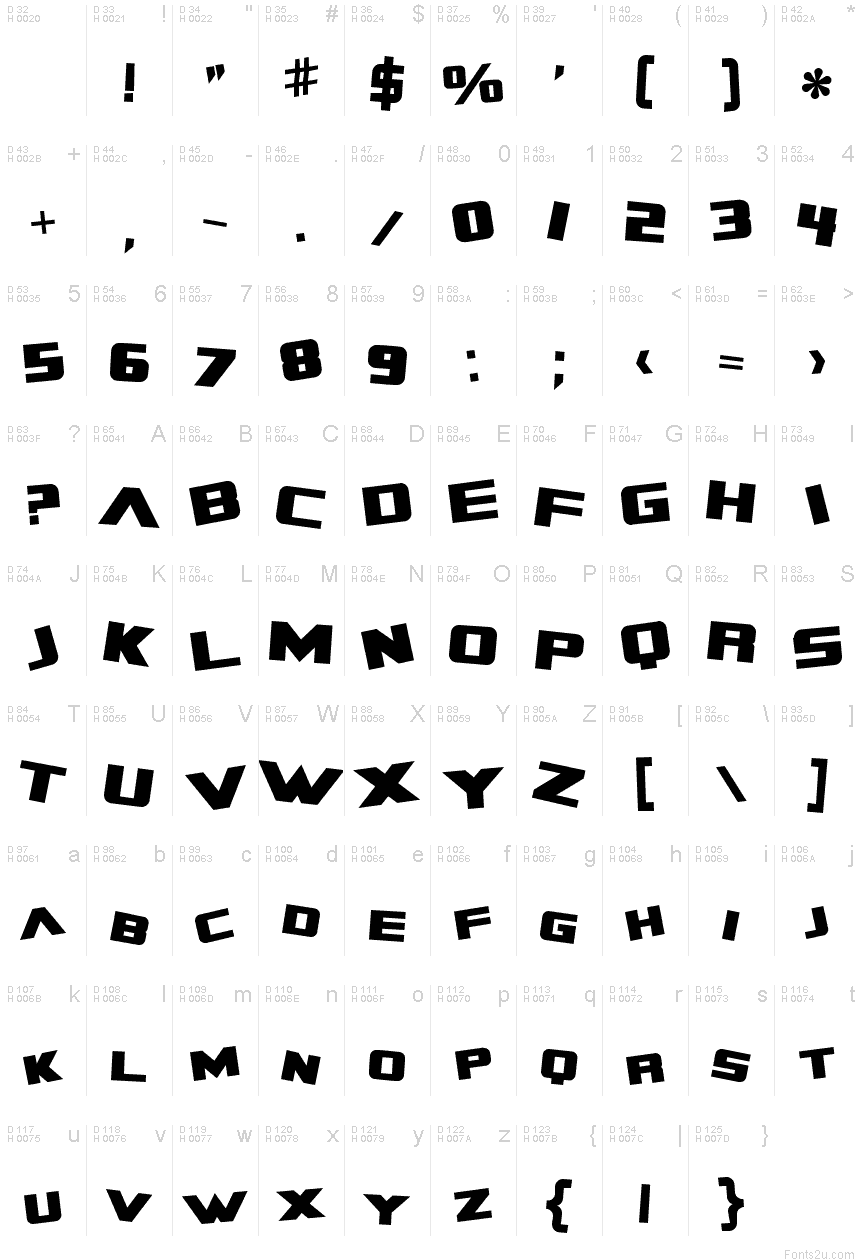
Zero Gravity Extended Bold von ShyWedge ist eine kostenlose Sci-Fi-Display-Schrift mit dem eigenwilligen Charme der Arcade-Ästhetik der späten 90er Jahre. Die Versalien sind breit, blockartig und leicht verzerrt; schräge Schnitte und eine unausgewogene Balance lassen die Schrift fast schwebend wirken, während ihre massiven Formen für Bodenhaftung und Ausdrucksstärke sorgen.
Damit eignet sie sich perfekt für Gaming-Logos, Sci-Fi-Poster, Mixtape-Cover, Zine-Überschriften und Titel, bei denen ein kurzes Wort einen energetischen, futuristischen Kick braucht. Als kostenloser Font aus dem Jahr 1999 entfaltet sie ihre Wirkung am besten in kurzen Display-Anwendungen – besonders dann, wenn die Buchstaben selbst für Dynamik und einen leicht verschmitzten, futuristischen Vibe sorgen sollen.